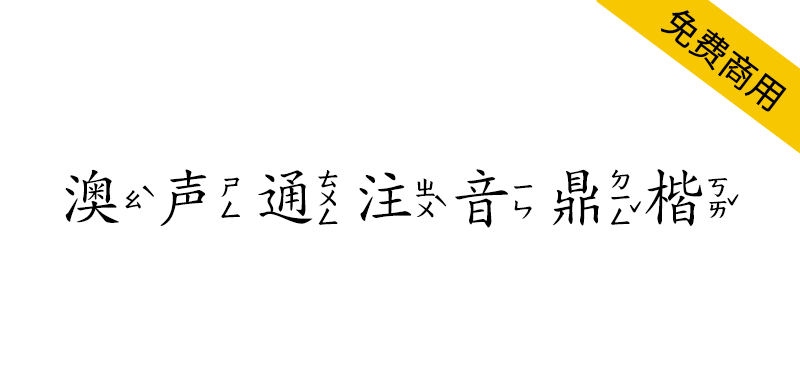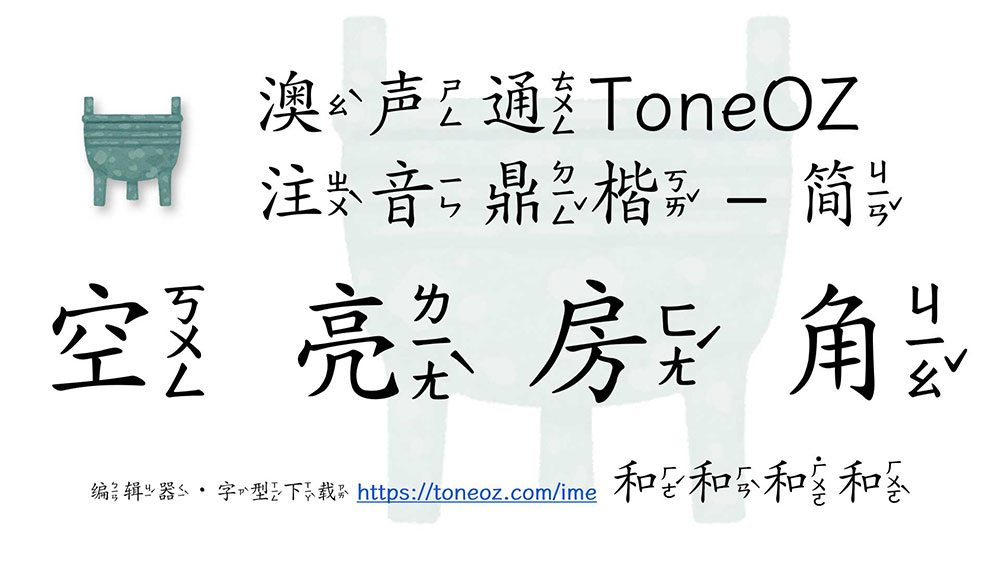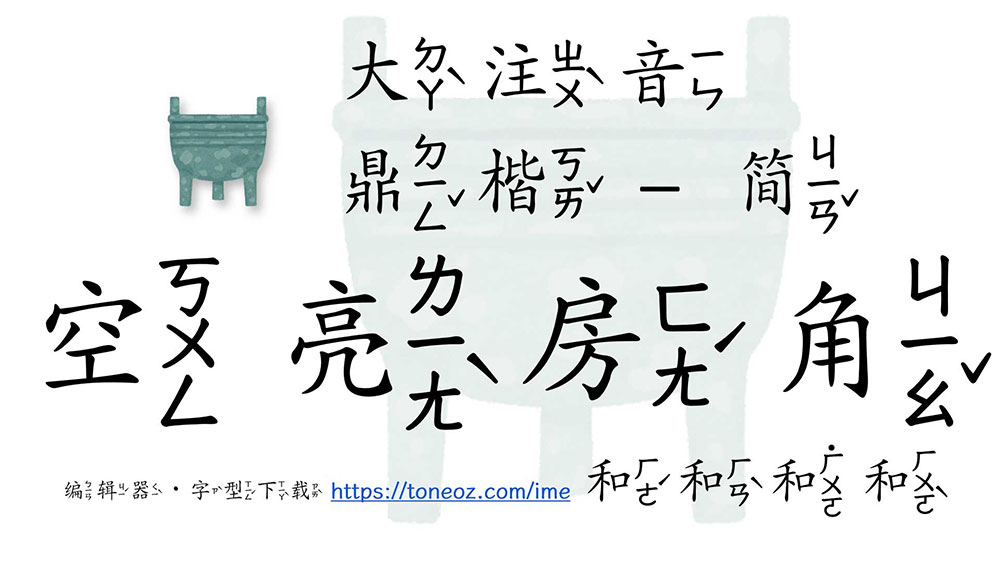
澳声通注音鼎楷是一款基于文鼎PL简中楷的标准楷体台湾注释音字型,免费商用,满足中文现场教学需求
注意:大注音版的注音很大,适合标题,注音部分可能会与邻近字重叠,使用时请斟酌搭配字距行距或加上空白使用。
澳声通小注音鼎楷 ToneOZ-Zhuyin-Kai-Simplified
澳声通大注音鼎楷 ToneOZ-ZhuyinW-Kai-Simplified